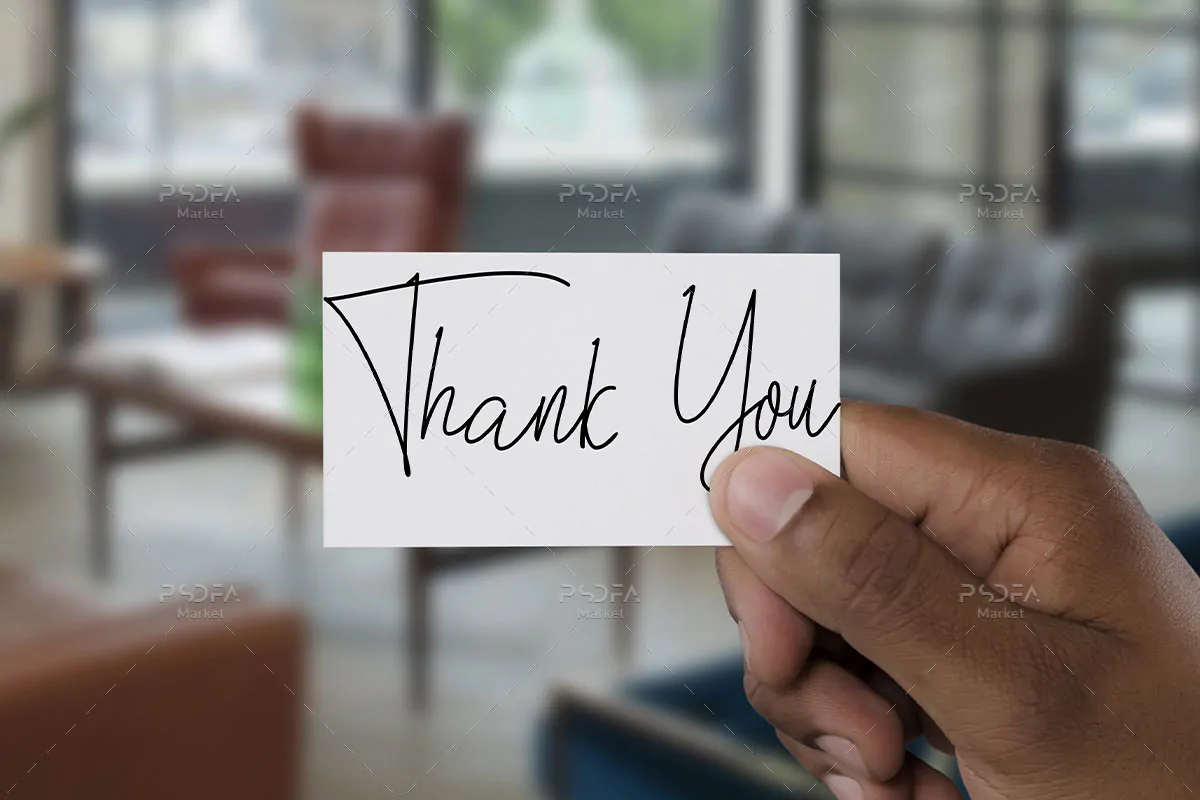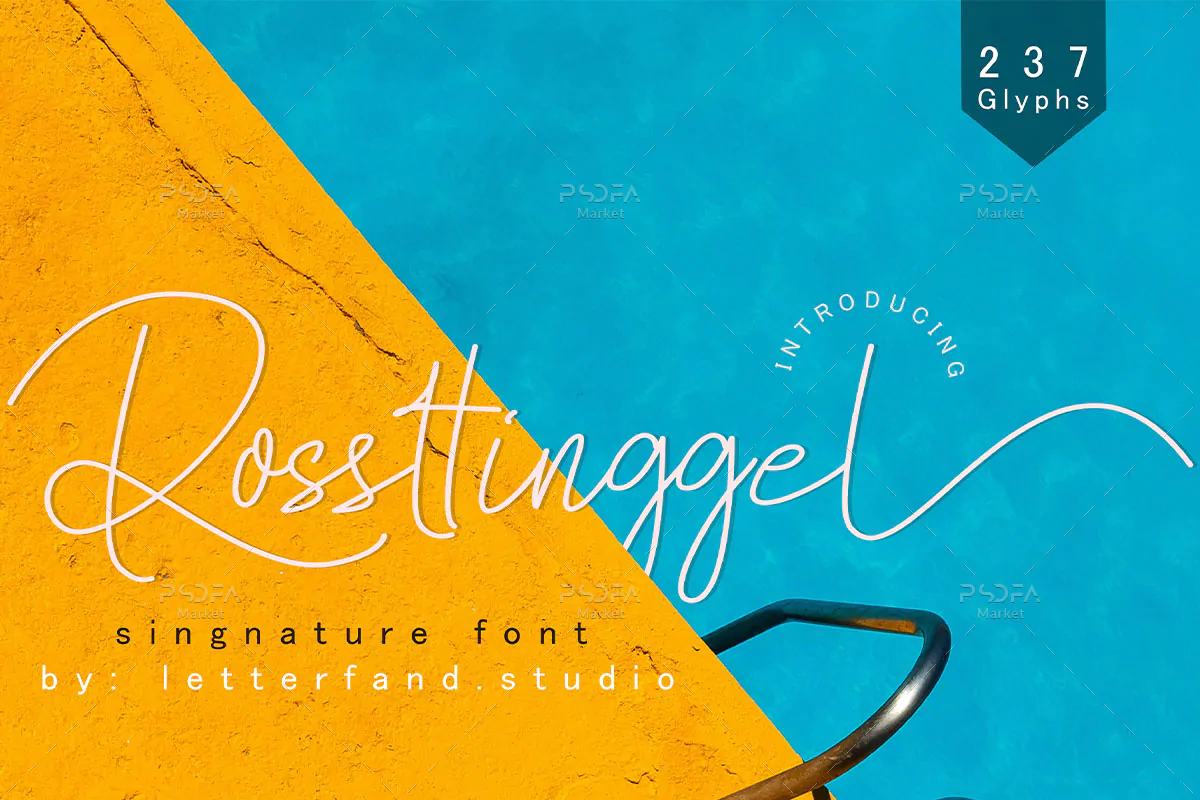
فونت رمانتیک دستنویس و باریک Rossttinggel
فونت رمانتیک دستنویس
فونت رمانتیک دستنویس و باریک Rossttinggel یک قلم انگلیسی فوق العاده زیبا است که مناسب جهت استفاده در طرح و پروژههای گرافیکی مختلف میباشد. این فونت زیبا با وزن معمولی طراحی شده است که میتوانید از آن در طراحی انواع پوستر، کار تبریک، بسته بندی محصولات، طرحهای رمانتیک ولنتاین، پست و استوری رسانههای اجتماعی، پوستر، بنر و … استفاده کنید.